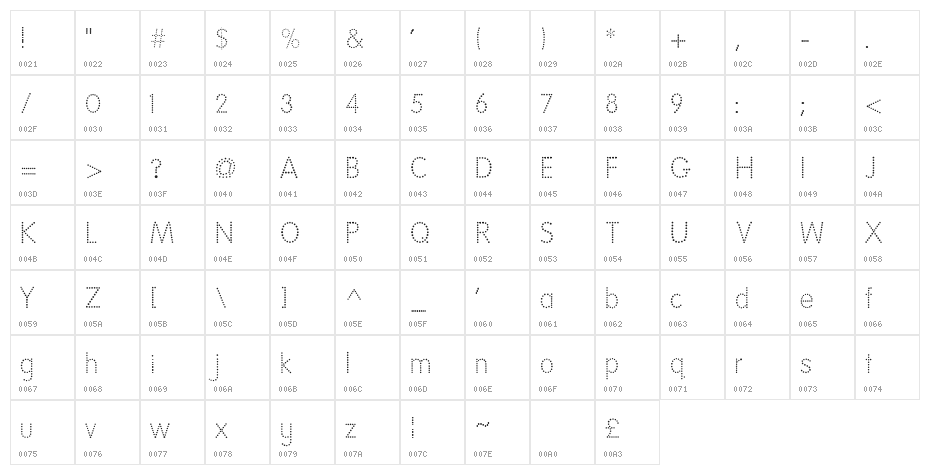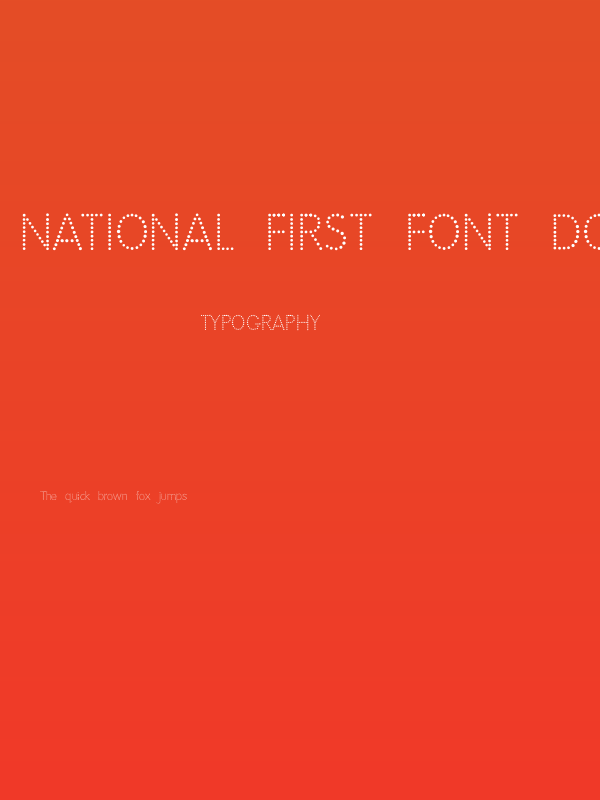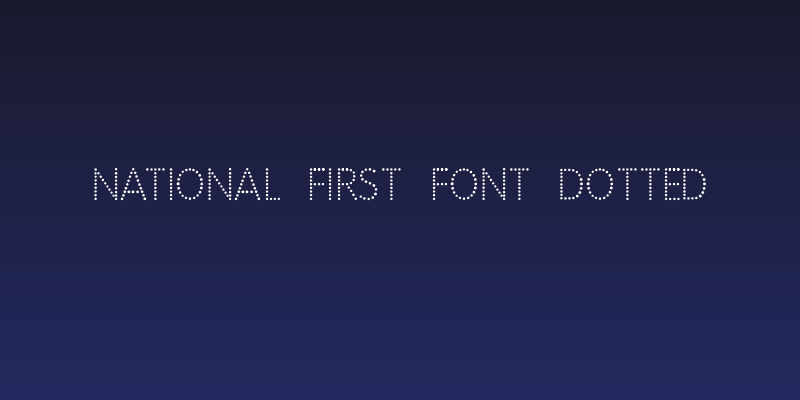
National First Font Dotted Font
✎ Dotted
| 使用场景 | Headlines, Logos, Creative projects |
| 推荐项目 | Ideal for educational materials, children's books, creative posters, and digital designs that require a unique and engaging typeface. |